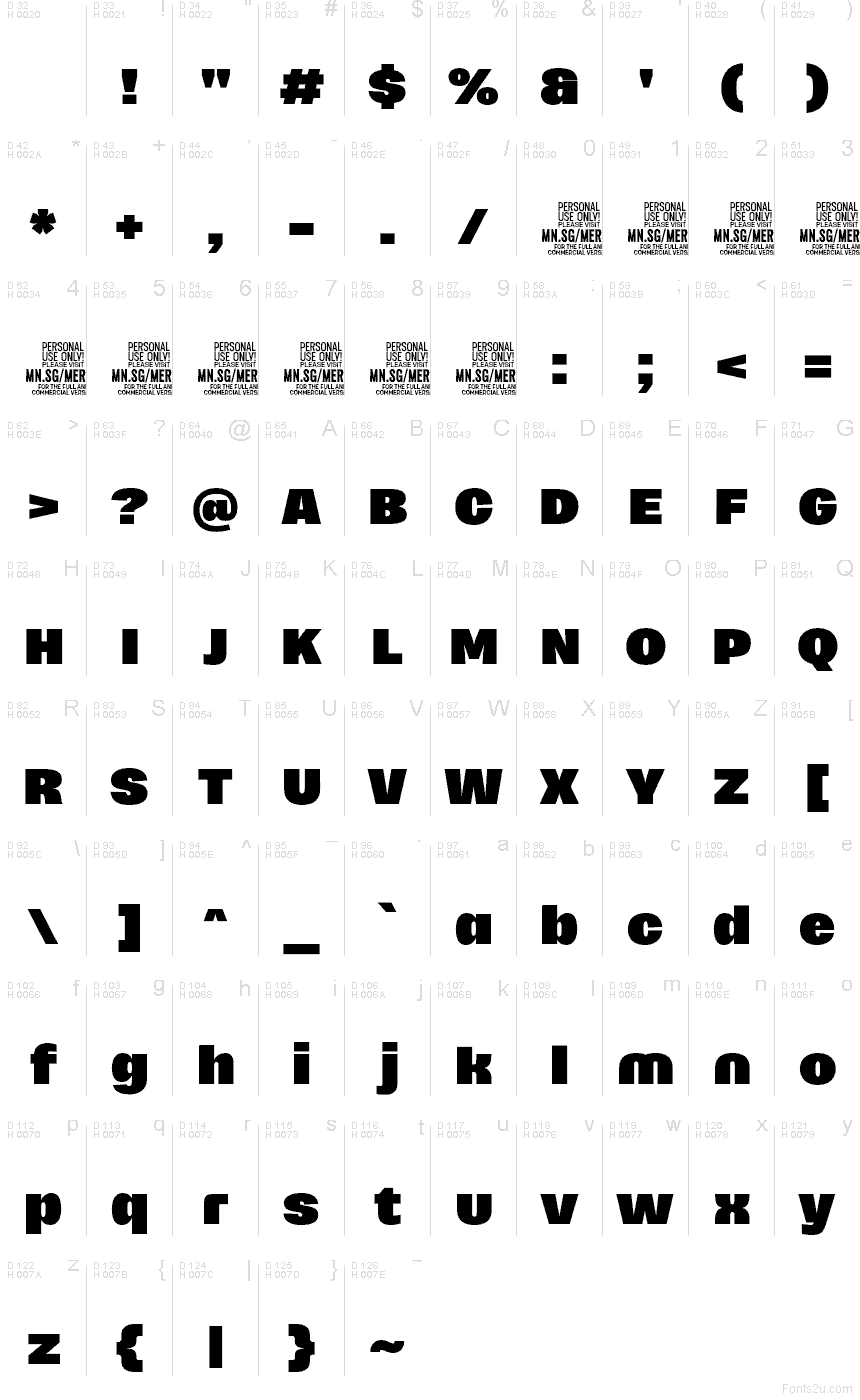
Merica Futurist PERSONAL USE Black
Merica Futurist von Mans Greback AB ist eine futuristische, serifenlose Schrift, die mit der rohen Wucht von Sci-Fi-Schriftzügen aus vergangenen Jahrzehnten überzeugt. Die Buchstaben sind groß, massiv und auf das Wesentliche reduziert; eine Mischung aus weiten Kurven und kantigen Schnitten verleiht dem Alphabet einen Look, der gleichzeitig nach Weltraumzeitalter und industrieller Ästhetik aussieht.
Die Schrift eignet sich hervorragend für Plakattitel, Albumcover, Game-Branding, Sportgrafiken und auffällige Verpackungen, bei denen ein kostenloser Font mit einer kompakten, ausdrucksstarken Präsenz gefragt ist. Setzen Sie ihn am besten für kurze Schlagzeilen, Titelkarten oder Monogramme ein, da die schweren Formen und der prägnante Rhythmus besonders bei knappen Texten zur Geltung kommen.